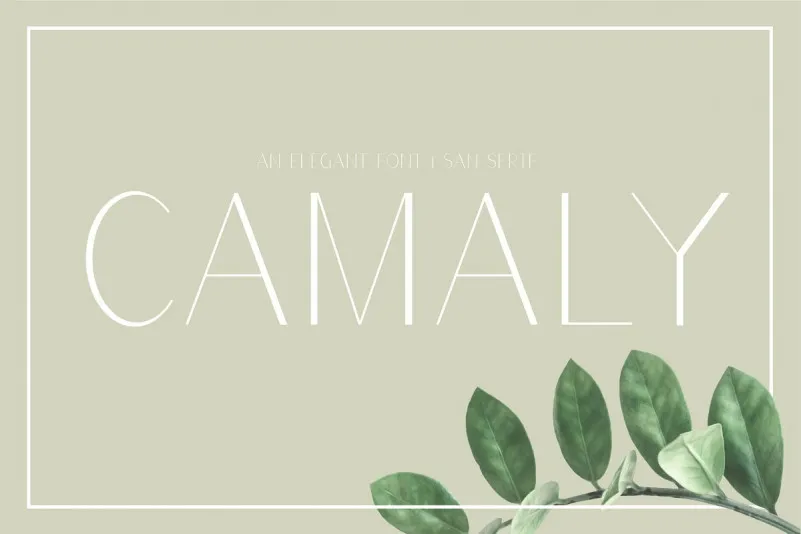
Camaly Sans Serif Font – Download Grátis
A fonte Camaly Sans Serif é uma elegante tipografia sans serif criada pelo designer 24Design para quem busca uma solução perfeita para estilos modernos e clean. Com um design minimalista mas afiado, ela é a escolha ideal para ambientes de negócios modernos e profissionais que valorizam sobriedade e clareza ao mesmo tempo em que procuram contraste visual para destacar informações importantes. Através da sua simplicidade, Camaly oferece um tipo poderoso que se destaca tanto na impressão quanto na tela digital. Com sua personalidade assertiva, esta fonte é perfeita para textos de negócios e design editorial, proporcionando ao seu texto uma presença forte e moderna em qualquer formato ou meio. Sem dúvida, Camaly Sans Serif é a fonte certa para quem busca um equilíbrio entre elegância e simplicidade no seu trabalho visual.